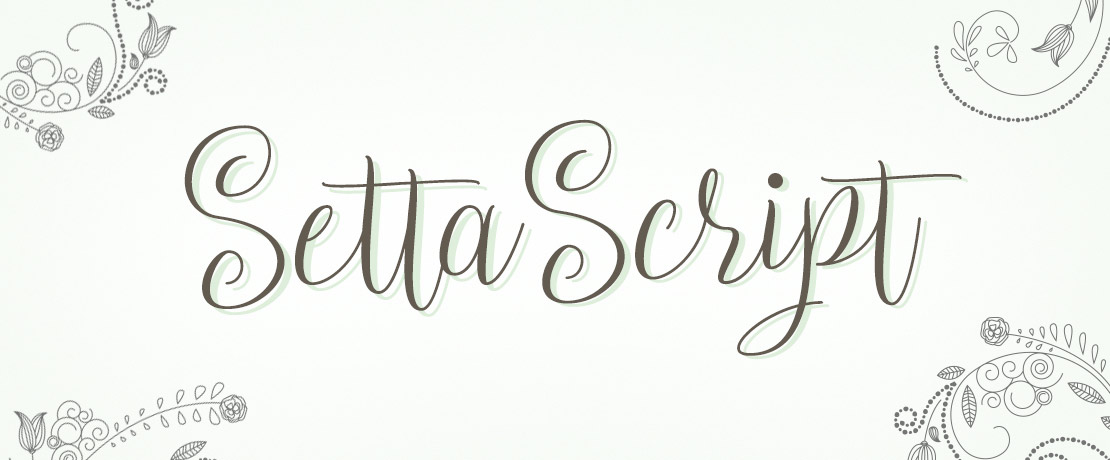
Setta Script
Setta Script ist ein kalligrafischer Font von Ianmikraz studio. Der Zeichensatz kann kostenlos im Opentype- und TrueType-Format heruntergeladen werden.